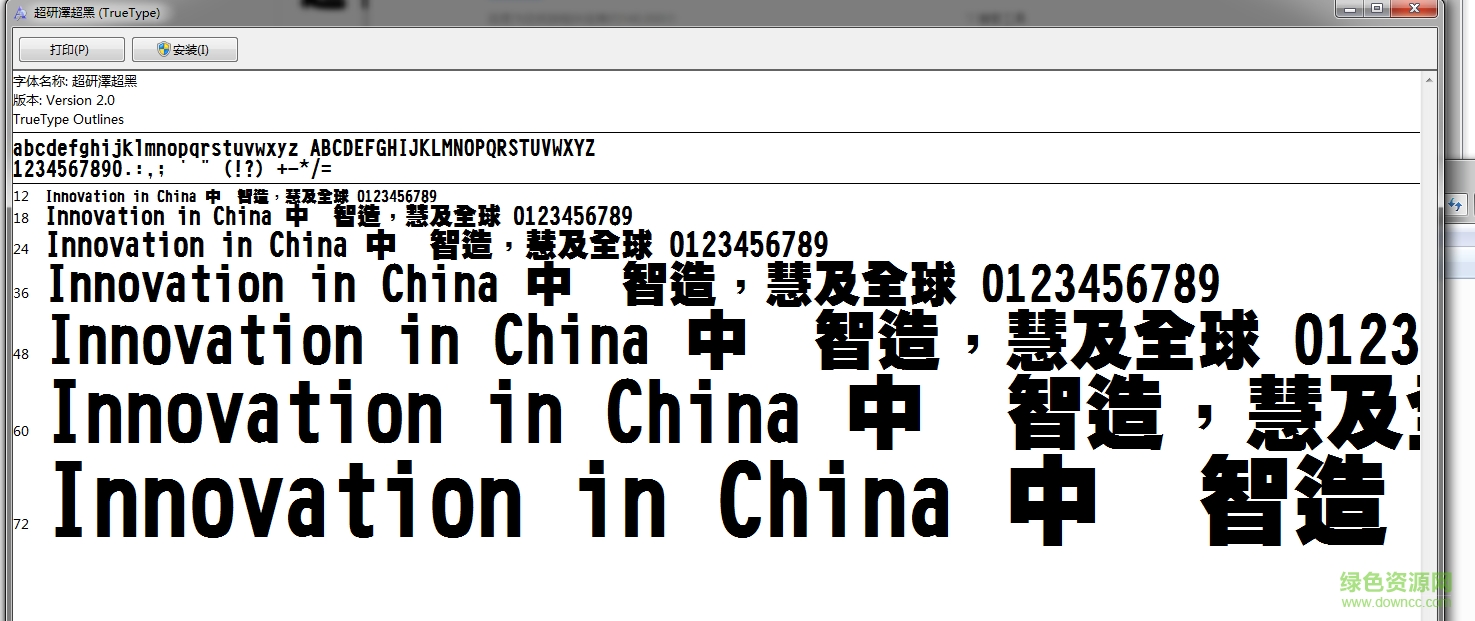
超研泽超黑体繁体
超研泽超黑体繁字体是一款许多朋友都在寻找的字体文件,改字体相对与其他字体更加的透黑、也较粗厚实,在PS、海报等处都受到了广泛的使用,需要的用户快到绿色资源网下载体验吧
超研泽超黑体繁预览
超研泽超黑体繁字体
超研泽超黑体繁字体介绍
超研泽超黑体繁字体是生活中使用较多的字体,整体效果很黑,字体的线条粗,给人美观